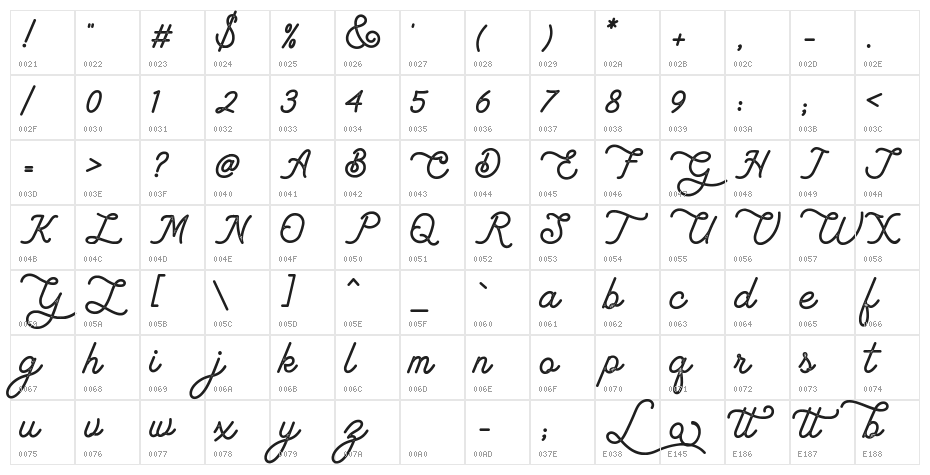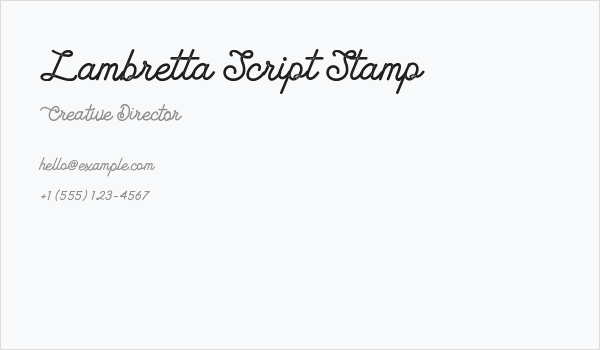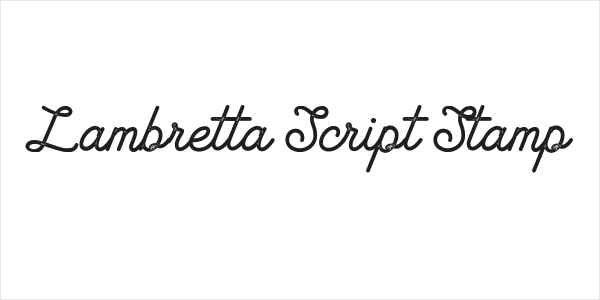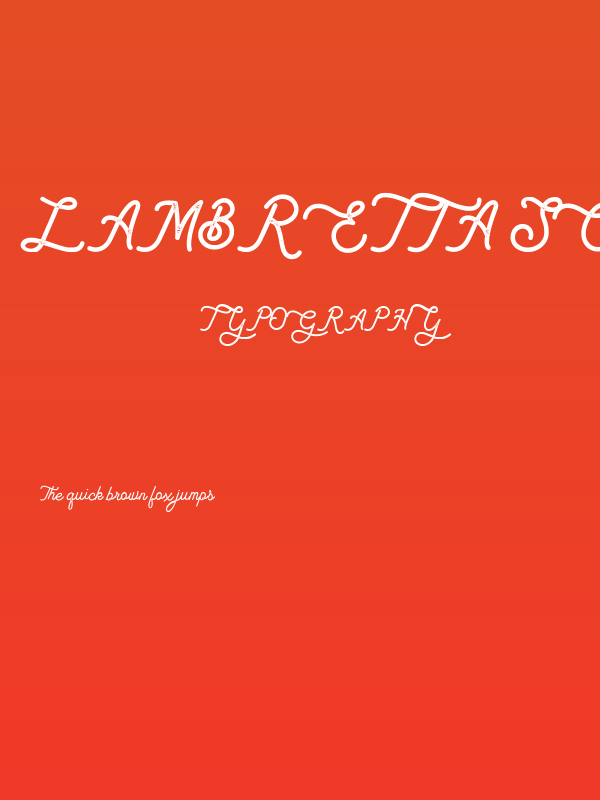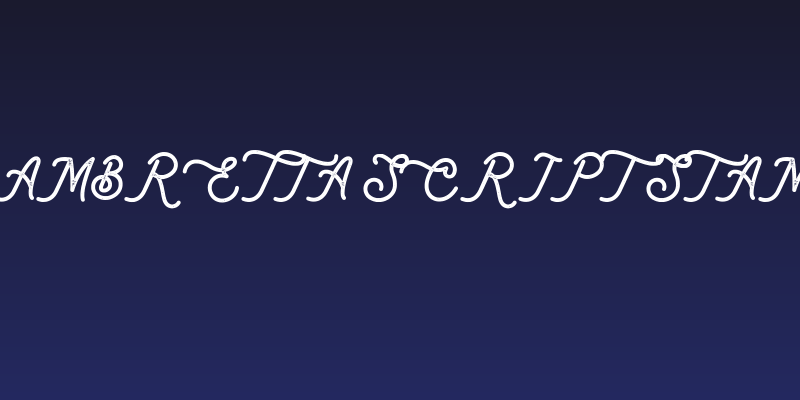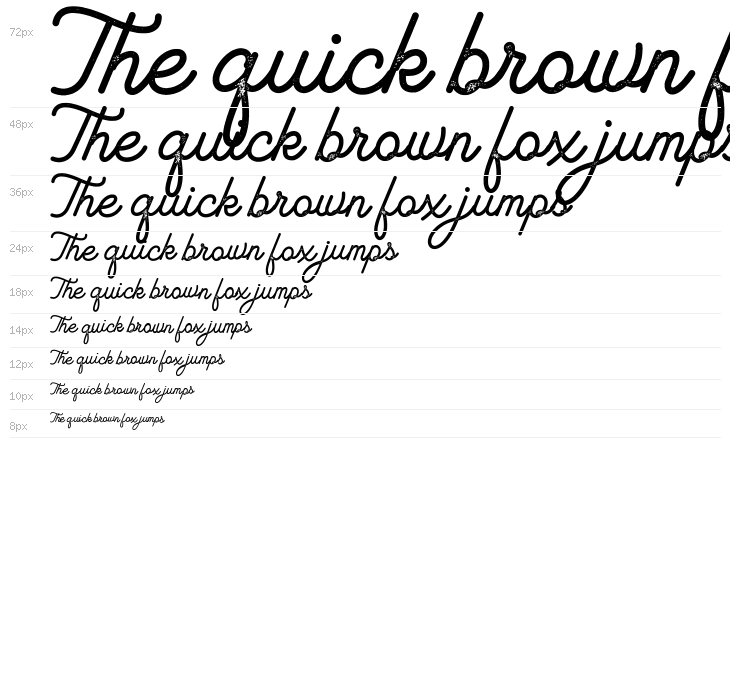
Lambretta Script Stamp Font
| Caso d'uso | Logos, Invitations, Posters |
| Progetti proposti | Ideal for vintage-themed designs, wedding invitations, branding for artisanal products, and retro posters. |